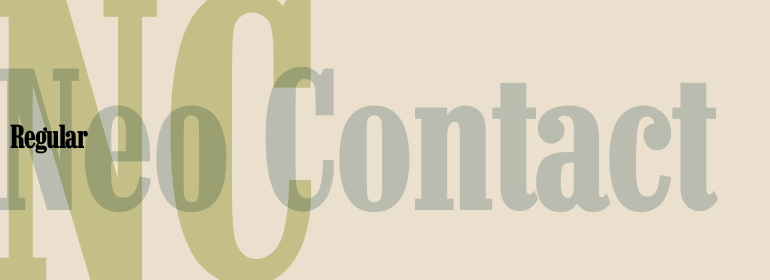
Neo Contact™
Neo Contact is the typeface used on the packaging of Marlboro cigarettes (Marlboro Reds," the main line of the brand). The typeface is bold and condensed, designed in the Egyptienne style. Egyptienne types were first designed in the 1800s, as type founders - especially in the westward-expanding United States - began to dream up newer, bolder styles of letters for advertising usage. During the 1800s, it became increasingly important for businesses to set themselves, and their products, apart from competitors. This desire has remained with corporations, as well as with advertisers and designers, into the 21st century.
In addition to cigarette packaging, Neo Contact (as part of Marlboro's branding efforts) can be seen on numerous items, including Ferrari's F1 racers, and at Formula 1 race tracks.
The letters in Neo Contact are filled with personality. Their forms display two distinct weights of line, and the serifs are made up of tiny, strict slabs. Ball terminals round out the design. Neo Contact is a complete font, with a complete western character set.
Typefaces in the Egyptienne style proceeded the development and distribution of larger, crazier wood typefaces, but also share many similarities with these descendents. More traditional, text faces in the Egyptienne manner are also available from Linotype GmbH (e.g., Adrian Frutiger's Egyptienne F). On the opposite end of the spectrum, we offer interesting, personality-filled wood display types, like Ponderosa as well."